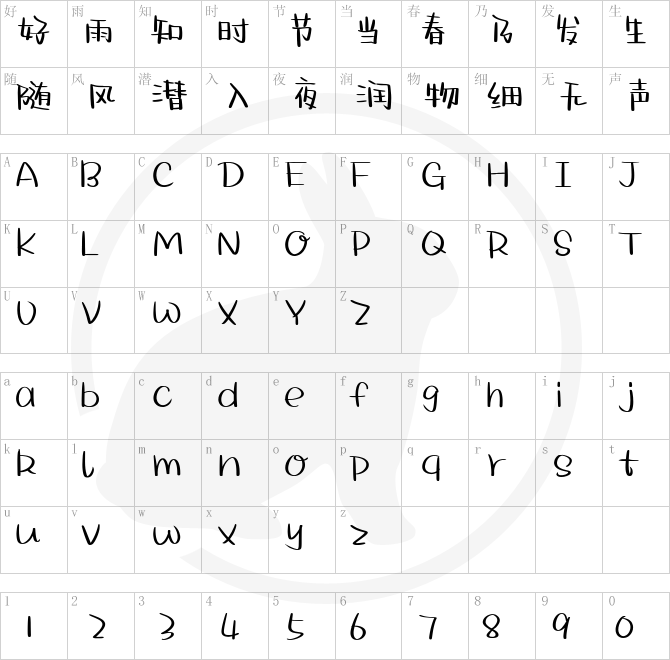
YEFONTChunRiGongYuanTi
YEFONTChunRiGongYuanTi,这款字体结构工整、笔画清晰,兼顾美观与易读性,适用于标题、正文、海报、包装、LOGO 等多种场景。字形优雅稳定,风格百搭耐看,适配日常排版与创意设计,让文字呈现更舒适、更具质感。YEFONTChunRiGongYuanTi一笔一画,皆是细节,以均衡的比例、流畅的线条打造舒适视觉体验,字形端正大气,风格简约现代。无论是商业设计、品牌宣传还是日常排版,都能轻松驾驭,让文字更有格调与力量。YEFONTChunRiGongYuanTi字体下载。
• 字体名称:YEFONTChunRiGongYuanTi
• 字体全名:也字工廠春日公園體 標準